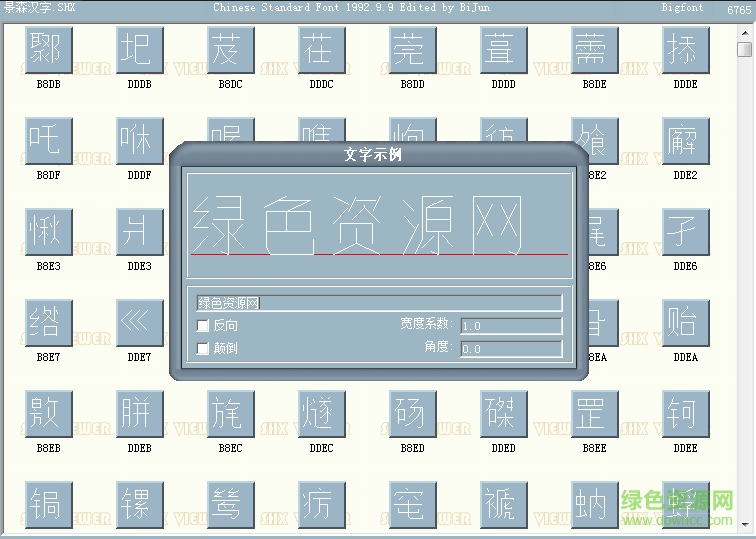
景森漢字.shx是一款專為經(jīng)常用到cad軟件的朋友準(zhǔn)備的一款中文cad字體,字體外形非常完美,如果您喜歡這款字體,或者是電腦缺失這款字體,都可以來(lái)綠色資源網(wǎng)下載安裝使用!
景森漢字.shx是一款字型優(yōu)美,字庫(kù)齊全的漢字cad字體,非常適合用于cad的創(chuàng)作,支持中文、數(shù)字和特殊符號(hào)的輸入,并且可以用于查看cad中含有該字體的圖紙!